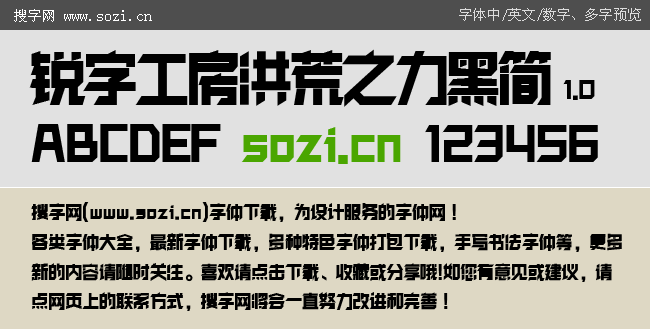
銳字工房洪荒之力黑簡(jiǎn)1.0
搜字網(wǎng)提供一款非常藝術(shù)的黑體銳字工房洪荒之力黑簡(jiǎn)1.0下載,銳字工房洪荒之力黑簡(jiǎn)是一款字形方正的銳字工房字體,該字體極具藝術(shù)感,簡(jiǎn)潔大方,適用于包裝印刷、廣告設(shè)計(jì)、平面設(shè)計(jì)、書(shū)籍報(bào)紙等領(lǐng)域。